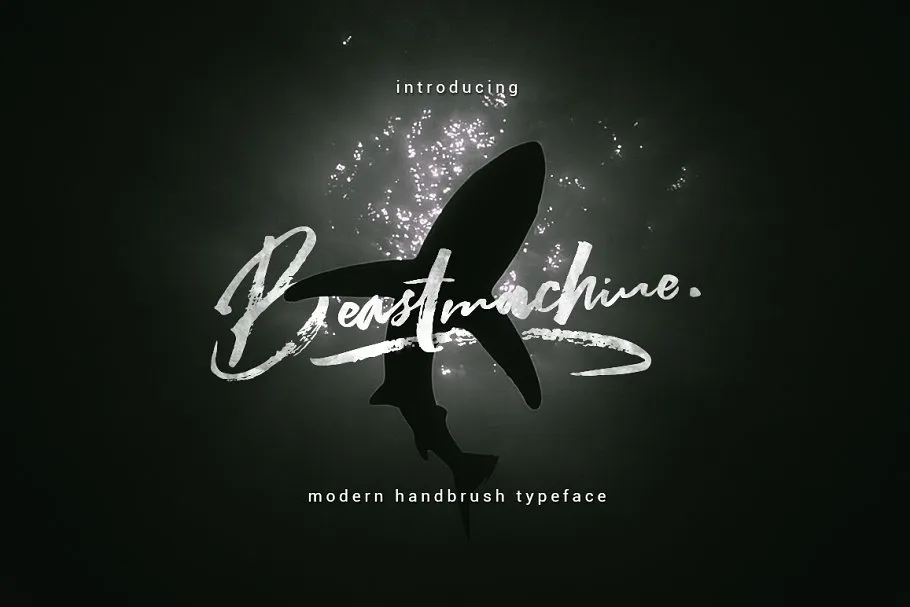
A Beastmachine Brush Font é uma nova sugestão para designers que desejam adicionar um toque único a suas criações digitais. Inspirada no estilo de escrita à mão, esta font script oferece linhas levemente irregulares e elegantes, proporcionando aos usuários uma experiência divertida e gratificante ao usá-la em projetos. Esta font é especialmente adequada para aplicativos como papelaria, logotipos, camisetas personalizadas, design de impressão, cabeçalhos de websites, molduras de fotos, flyers, capas de música, cartazes e rodapés nos sliders de imagens. Além disso, a Beastmachine inclui ligaturas padrão, o que dá ao seu projeto um aspecto mais natural e scriptado quando você tiver letras repetidas em suas criações. Com suporte multilíngue para caracteres acidentados para usuários internacionais, esta font também se destaca como uma opção versátil. A Hamilton é responsável por essa fonte, que oferece uma variedade de possibilidades semelhante à da sua experiência criativa. Composta com precisão e elegância, a Beastmachine Brush Font certamente vai inspirar seus projetos digitais para um novo patamar.